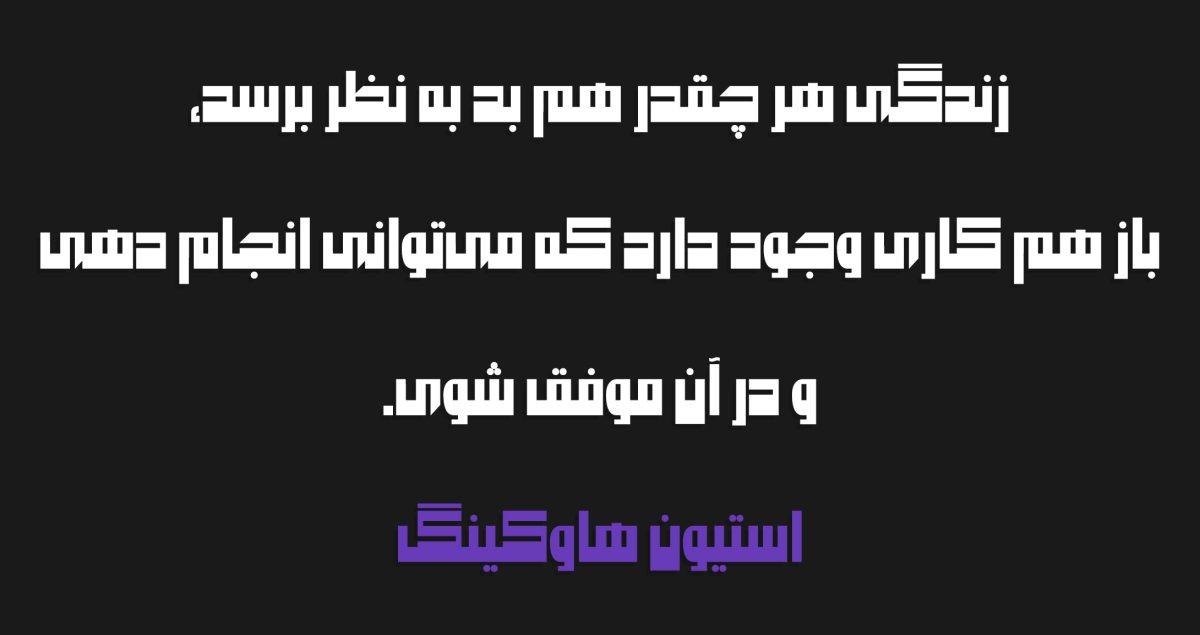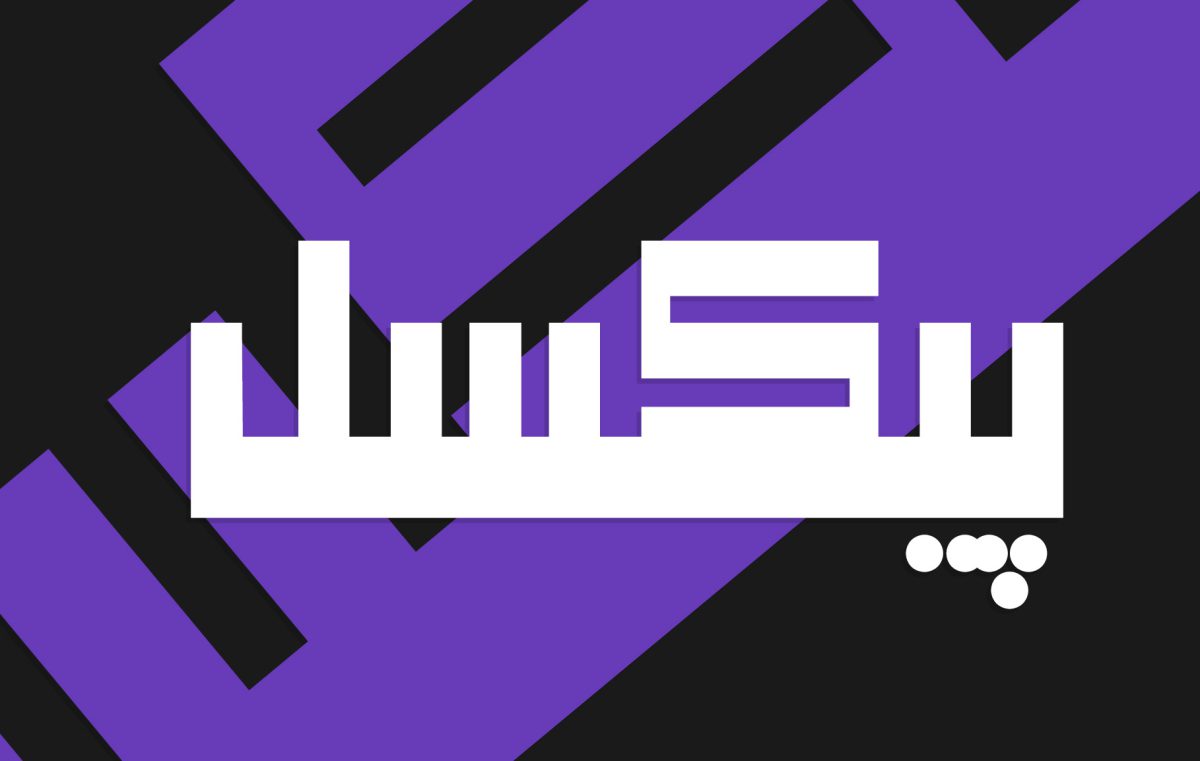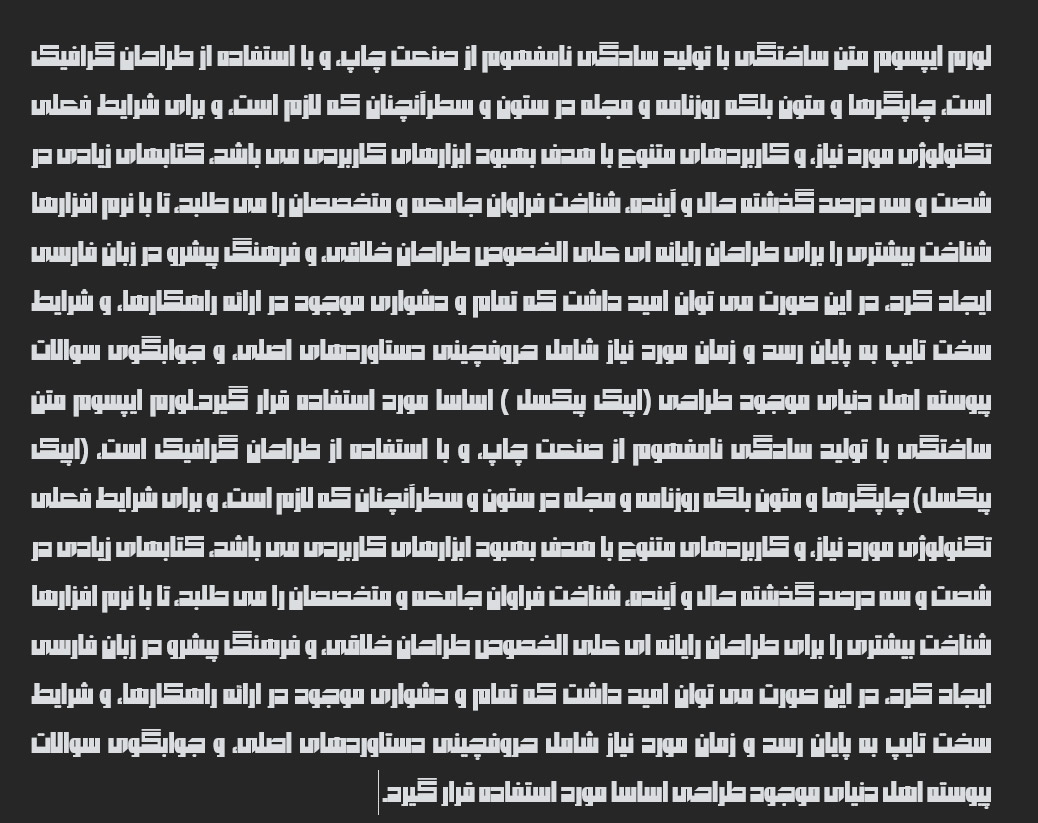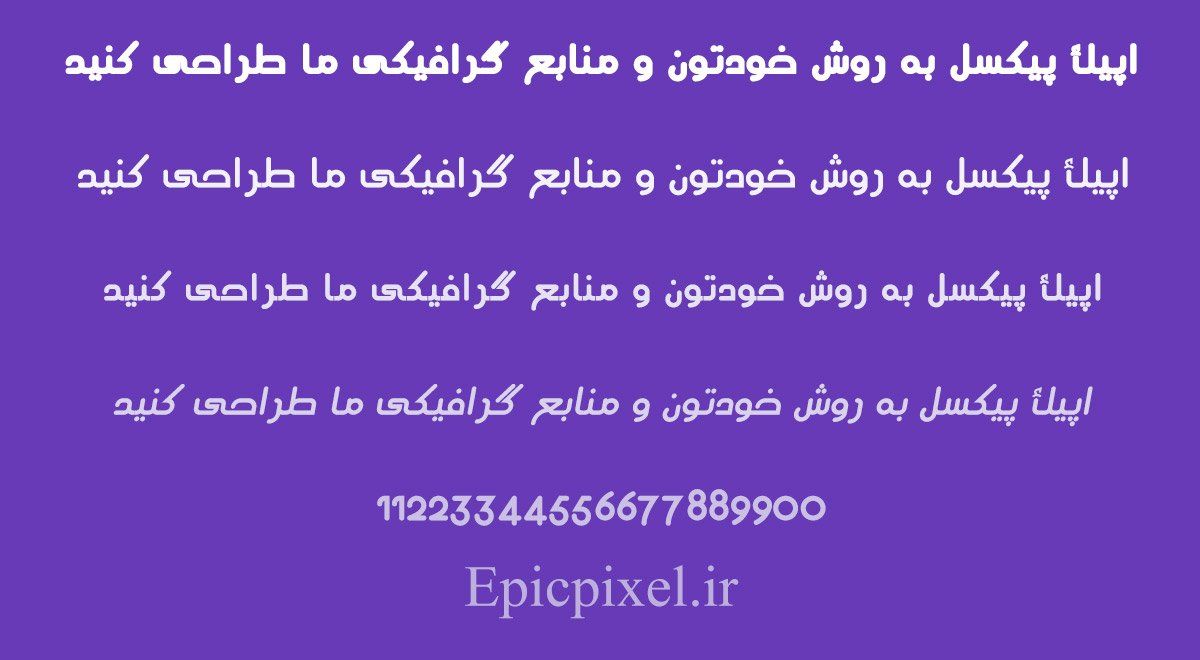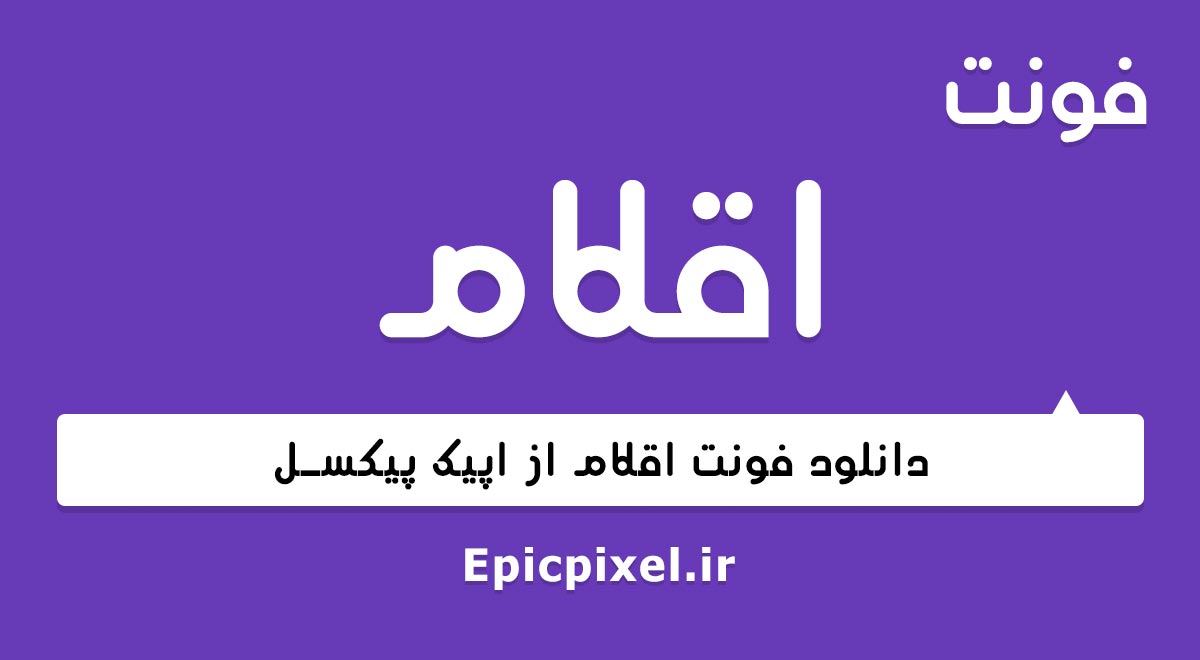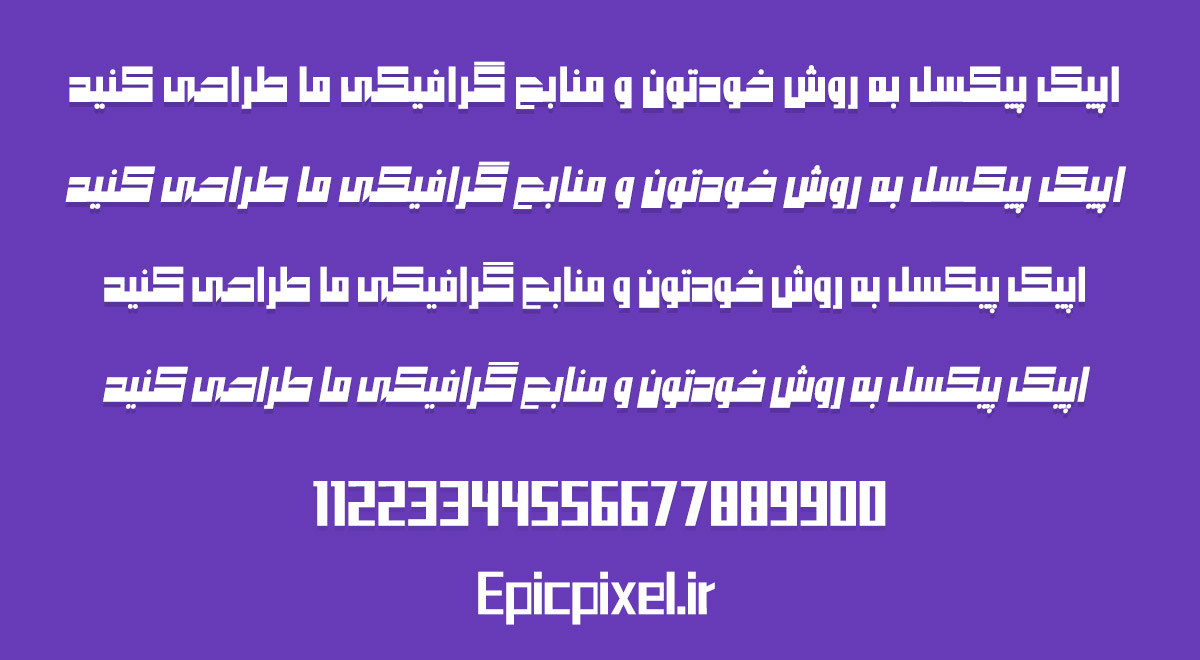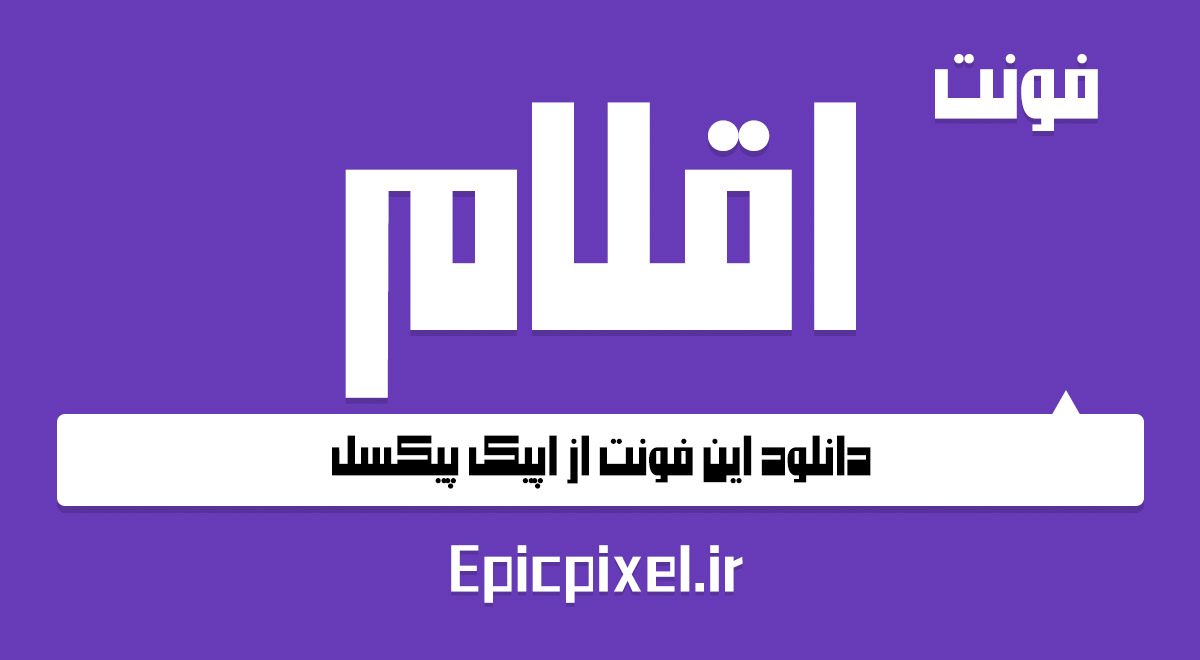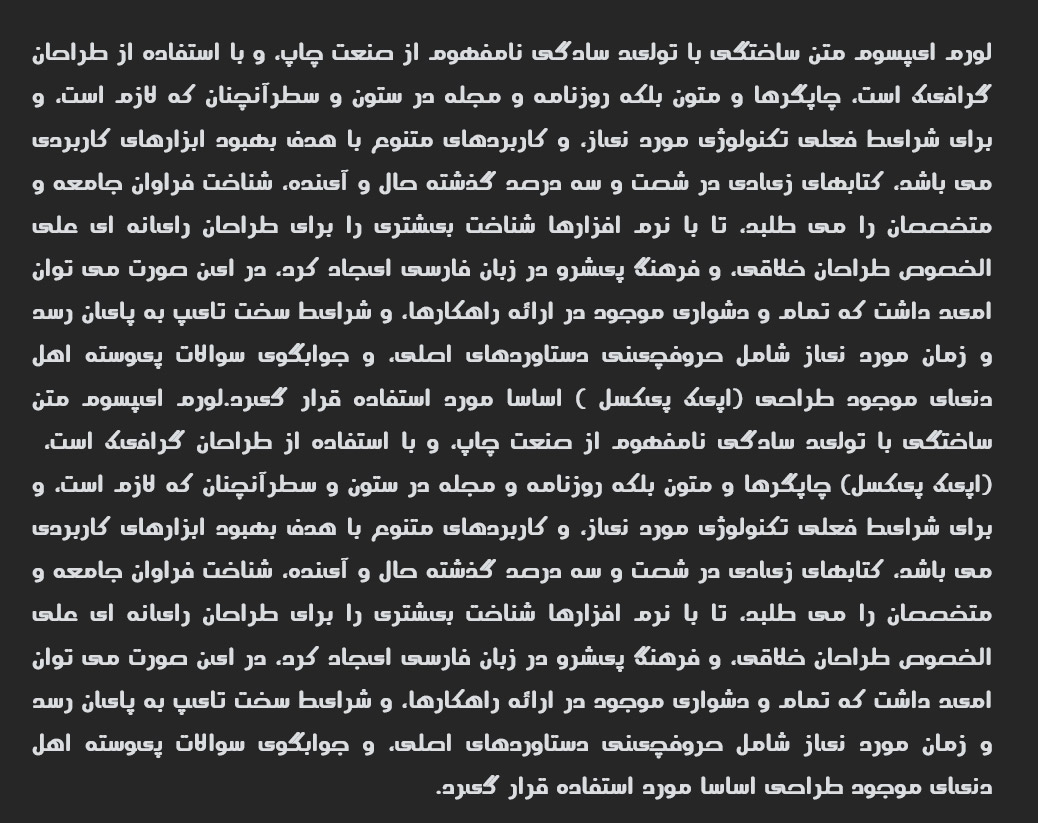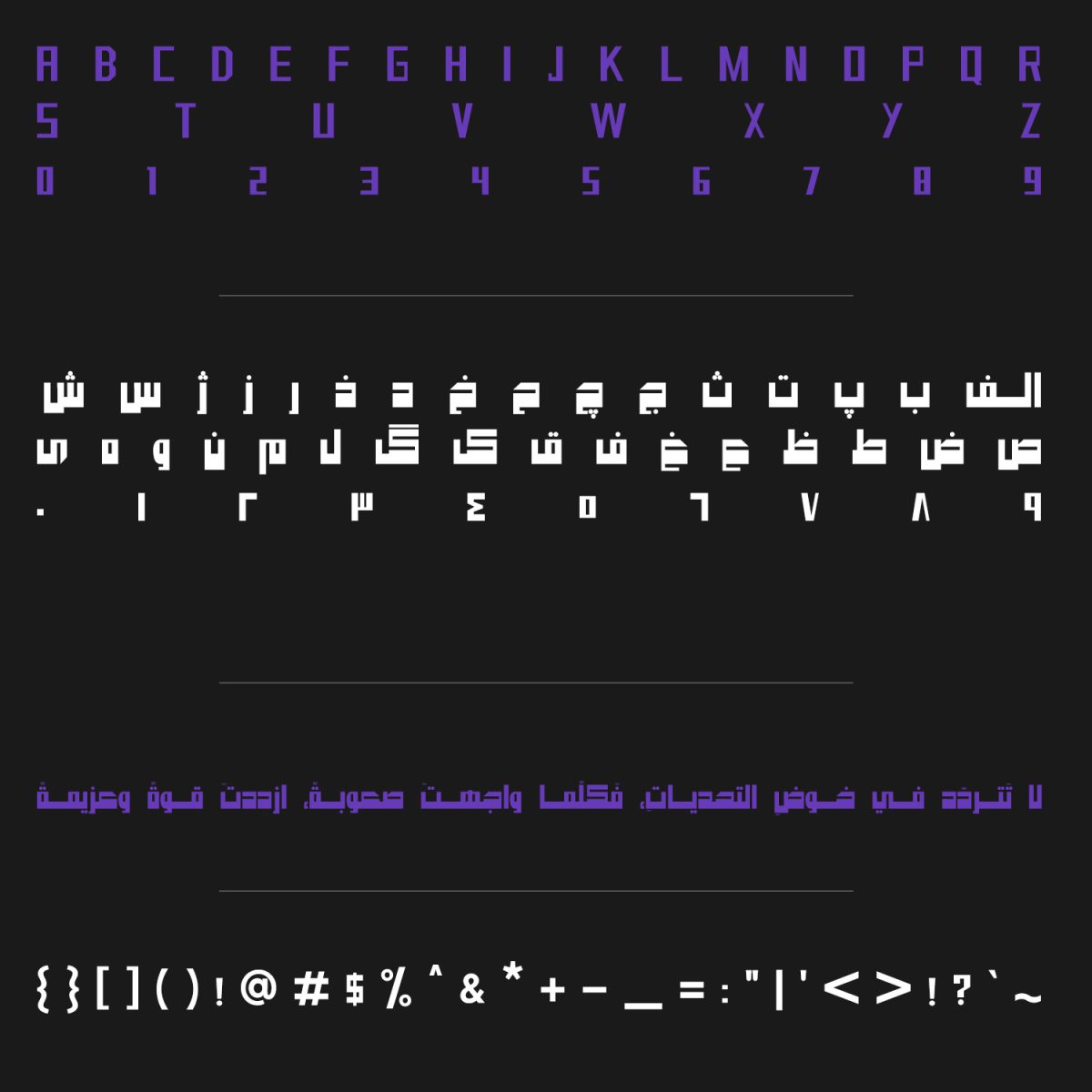
2 فونت اقلام فارسی Aqlam
دانلود رایگان مجموعه فونت اقلام (Aqlam) شامل دو فونت متمایز است: Aqlam Corner با ظاهری درشت، گوشه تیز و مربعی و Aqlaam با فرمی نرم و گرد. Aqlam Corner شامل حروف کامل فارسی، انگلیسی و عربی است، در حالی که Aqlaam حروف فارسی و عربی را پوشش می دهد اما برای ی وسط نیاز به استفاده از ی وسط عربی دارد. این فونت ها با طراحی زیبا و مدرن خود، برای طراحی های گرافیکی، متون ادبی، عناوین و پروژه های مرتبط با فرهنگ و هنر مناسب هستند و در سیستم عامل های ویندوز، iOS و اندروید قابل استفاده می باشند. این مجموعه با ارائه دو سبک متضاد، تنوع بصری مناسبی را برای طراحان فراهم می کند.
مجموعه فونت اقلام: دو سبک متمایز برای طراحی های فارسی و عربی
مجموعه فونت اقلام فارسی عربی (Aqlam)، یک مجموعه فونت دوگانه است که دو فونت با سبک های بصری کاملاً متفاوت را در بر می گیرد: Aqlaam و Aqlam Corner. این مجموعه با ارائه این دو فونت متضاد، انعطاف پذیری بالایی را برای طراحان در انتخاب سبک مناسب متناسب با نیاز پروژه فراهم می کند. فونت اقلام به صورت کلی به طراحی زیبا و مدرن معروف است و یک فونت عربی است که از زبان فارسی نیز پشتیبانی می کند، که آن را برای استفاده در هر دو زبان کاربردی می سازد.
فونت Aqlam Corner یک فونت درشت ، گوشه تیز و مربعی است که با خطوط تیز خود حالتی خاص را به مخاطب منتقل می کند و ظاهری قوی، هندسی و ساختارمند دارد. این قلم شامل حروف کامل فارسی ، انگلیسی و عربی بصورت کامل بدون کسری می باشد که آن را برای پروژه های سه زبانه جامع و کاربردی می سازد و نیاز به فونت های جداگانه را از بین می برد. قلم زيباي Aqlam Corner Bold توسط یک طراح/developer منتشر شده است و برای عناوین اصلی و طرح های نمایشی که نیاز به تأثیر بصری بالا و ظاهری قاطع دارند، مناسب است.
دانلوداما فونت Aqlaam یک فونت نرم و گرد است و معمولاً دارای خطوط نرم و منحنی است که به آن ظاهری لطیف و جذاب می بخشد و حسی دوستانه، هنری تر و روان تر را القا می کند. این فونت شامل حروف فارسی و عربی است. نکته مهم و قابل توجه در مورد این فونت این است که بدون حرف ی وسط فارسی ارائه شده است. برای نوشتن حرف ی وسط در این فونت و اطمینان از نمایش صحیح، باید از ی وسط عربی استفاده بشه که نیازمند توجه کاربر در هنگام تایپ است و یک نکته فنی برای استفاده از این فونت محسوب می شود.
فونت اقلام (Aqlaam)، با فرم نرم خود، به خوبی برای استفاده در متون ادبی، عناوین و طراحی های گرافیکی مرتبط با فرهنگ و هنر مناسب است. طراحی خاص این فونت آن را به گزینه ای مناسب برای پروژه هایی با محوریت زیبایی شناسی و احساسات انسانی تبدیل کرده است و به انتقال حس در متن کمک می کند. این فونت همچنین به دلیل خوانایی خوبی که دارد، در اندازه های بزرگ و کوچک به خوبی قابل استفاده است و به راحتی در اندازه های مختلف قابل خواندن و درک می باشد. اقلام انتخابی عالی برای طراحانی که به دنبال ایجاد آثار هنری با ظاهری خاص و دلنشین هستند و می خواهند متون خود را با زیبایی بصری همراه کنند. این مجموعه با ارائه دو سبک متضاد (تیز و گوشه دار در Aqlam Corner، نرم و گرد در Aqlaam)، ابزارهای متنوعی را برای نیازهای مختلف طراحی در اختیار طراحان قرار می دهد و امکان ترکیب این سبک ها در یک پروژه نیز وجود دارد.
کاربردهای مجموعه فونت اقلام در طراحی گرافیک
با ارائه دو سبک متمایز (تیز و گوشه دار در Aqlam Corner، نرم و گرد در Aqlaam)، مجموعه فونت اقلام کاربردهای متنوعی در طراحی گرافیک دارد و به طراحان امکان می دهد تا از سبک های متناسب با پیام و هدف طرح خود استفاده کنند. فونت Aqlaam برای استفاده در متون ادبی، عناوین و طراحی های گرافیکی مرتبط با فرهنگ و هنر و پروژه هایی با محوریت زیبایی شناسی و احساسات انسانی مناسب است و به دلیل خوانایی خوبی که دارد، در اندازه های مختلف به کار می رود و حس لطافت را منتقل می کند. فونت Aqlam Corner با ظاهر درشت و گوشه تیز خود، برای عناوین، پوسترها، بنرها و لوگوتایپ ها که نیاز به تأثیر بصری قوی و ظاهری قاطع دارند، گزینه ای عالی است. این مجموعه با پشتیبانی از حروف فارسی، انگلیسی و عربی، برای پروژه های چندزبانه نیز کاربرد دارد و نیازهای زبانی متنوع را پوشش می دهد. به طور کلی، انتخابی عالی برای طراحانی است که به دنبال ایجاد آثار هنری با ظاهری خاص و دلنشین هستند.